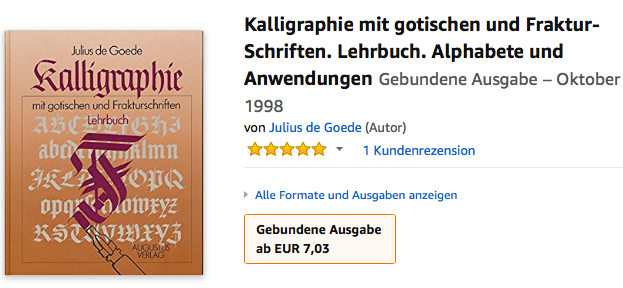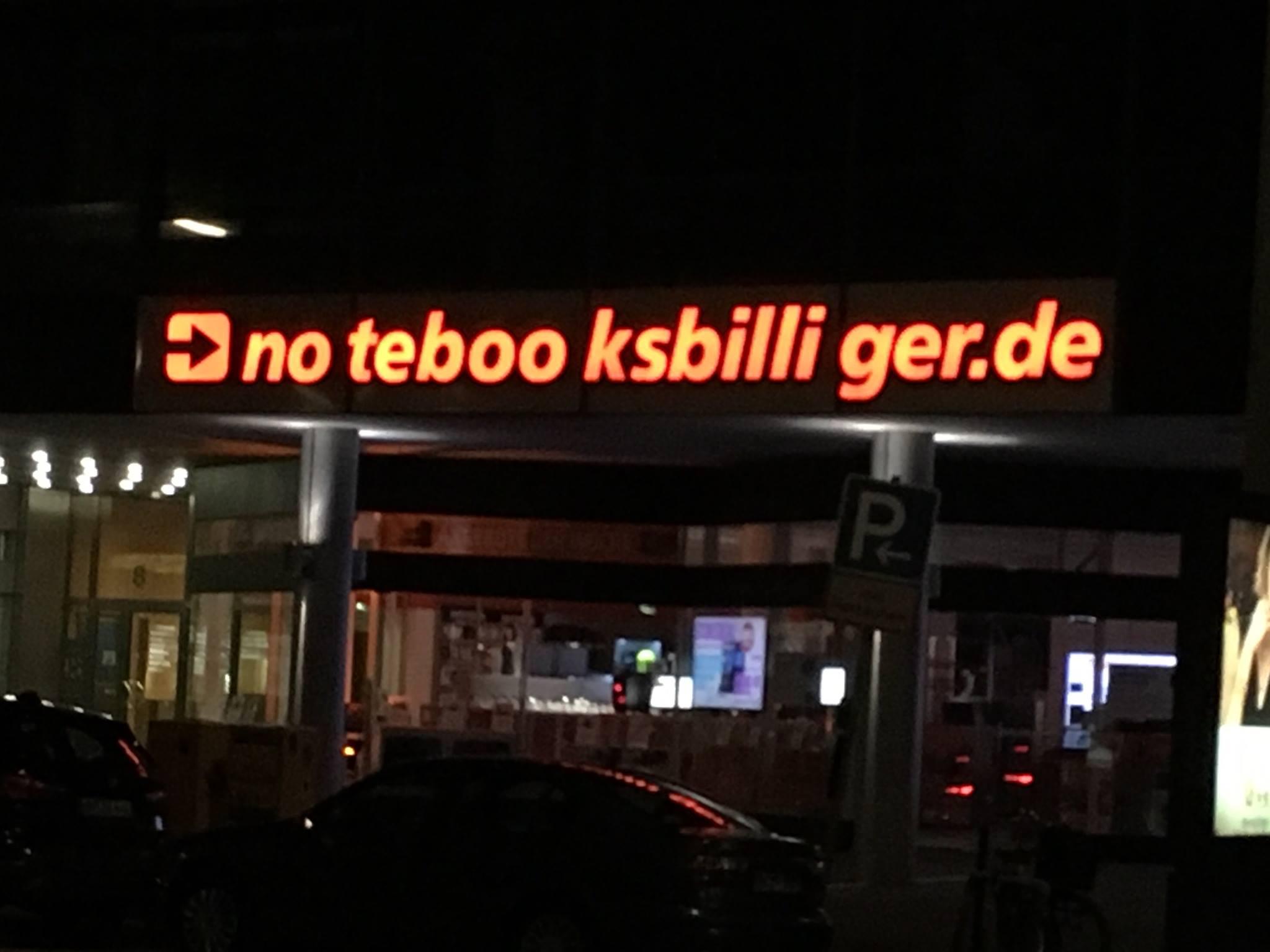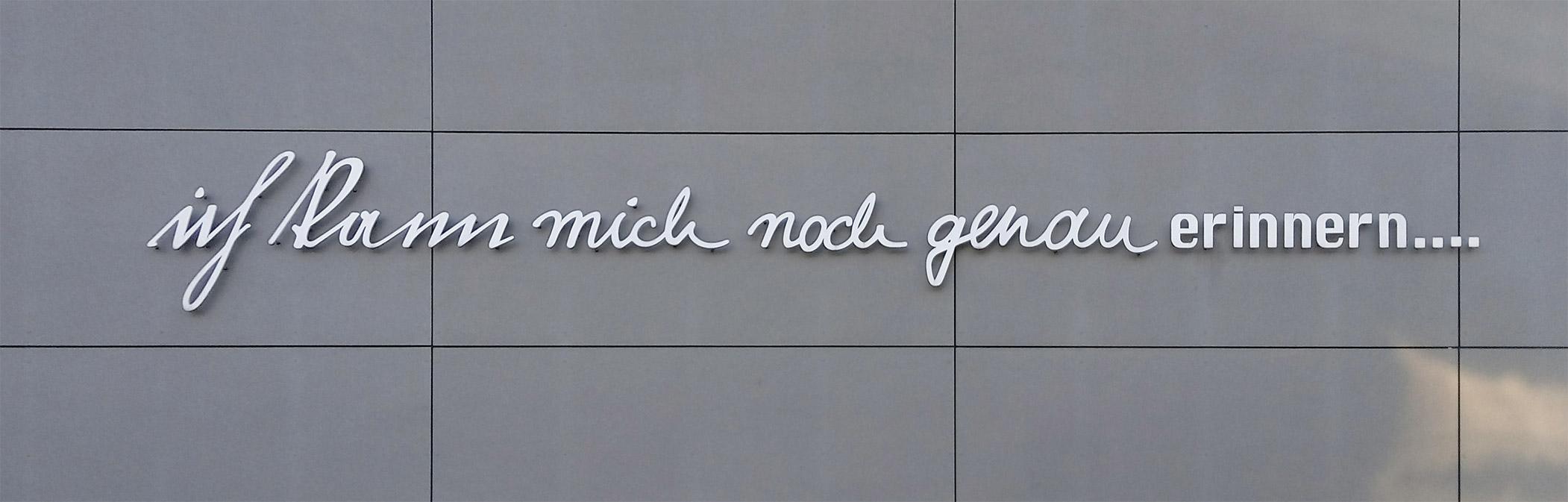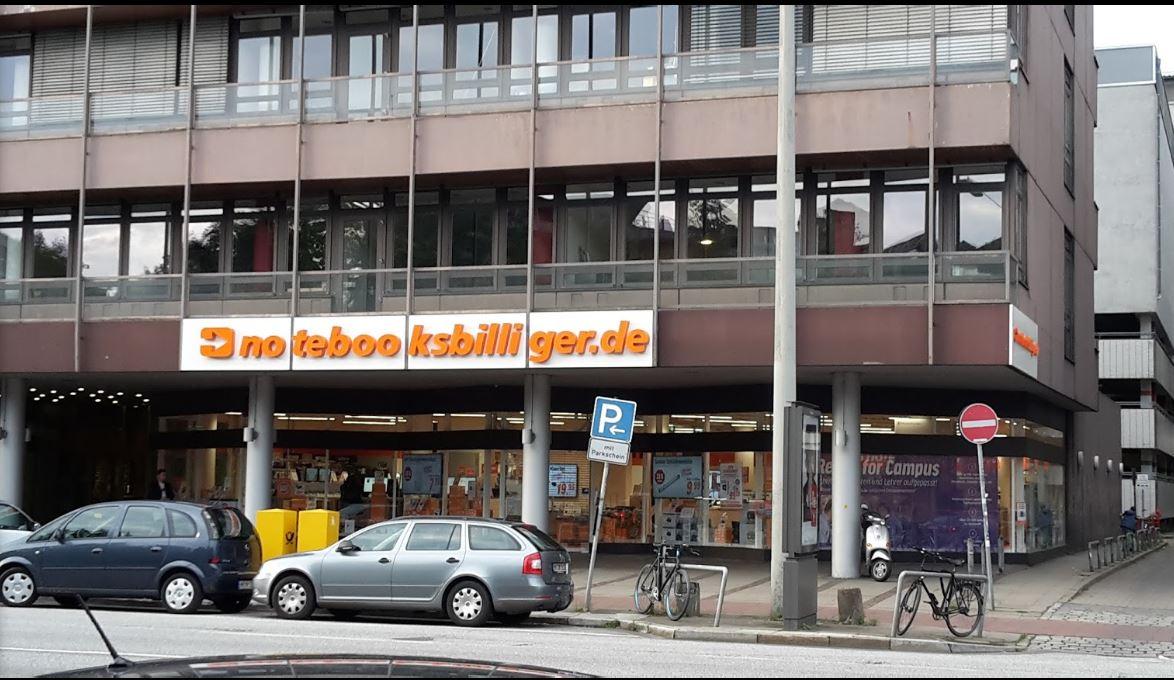
Kalligrafie ist anscheinend auch so‘ne coole neue Art von Lettering, äquivalent zu Letterpress im Nachbarstrang :-o
Ja genau – ist doch alles mit Schreiben und so. :nicken:;-)
Ne, gibt’s schon länger – seit 22 Jahren ungefähr 8-)
Ich dachte du wolltest auf das f statt ph hinaus  :-)
Nö, des Rätsels Lösung ist die Fugenbreite der Platten, auf denen die Leuchtschrift angebracht ist. Hätte man sicher auch schöner lösen können.
Nun ja, schon irgendwie schlimm... ABER kann es nicht sein, das gerade dieses Rätsel: "no teboo...??? Wie jetzt,. kein Taboo?" dazu führt, dass viele stehen bleiben und einige Zeit daran herumstottern, bis sie letztlich entdecken, das ist ein Laden von Notebooks billiger.de - und schon hat sich die URL im Hirn eingebrannt.
Und schon machen wir und andere Seiten, welche dieses Typo-"Missgeschick" zeigen wieder kostenlos Werbung für den Laden.
Ich würde mal sagen: Happy Accident...
Naja, man kann sich auch alles schön reden. Das wird sicherlich nicht so geplant sein. Wahrscheinlich war das die billigste und einfachste Lösung, weil diese Platten schon da waren. Man kann sich etwas einprägen und man möchte sich mit etwas beschäftigen, wenn es schnell und einfach wahrnehmbar ist. Irritationen können auch wirken, sollten dann aber auch offensichtlicher sein … Murks ist Murks
Das ist schon richtig, geplant ist das garantiert nicht, und Murks ist es auch. Schö reden wollte ich das nicht, sondern hatte eben das gefühl, dass solch stümperhafter Murks gelegentlich auch dafür gut ist, sich an so einen b esser erinnern zu können, und dann eben doch einen wirtschaftlich überraschenden Nebeneffekt hat.
Beispiel: in den frühen 1970er Jahren traf ich auf einen An-und -Verkauf-Laden, der eben auch ein ziemlich stümperhaftes Ladenschild hatte, auf dem dieses An und Verkauf teils horizontal, silbenweise, teils vertikal auf dem Schild verteilt war, und man über 3 Zeilen VER AKA NUF  lesen konnte. Auch das erschoss sich erst nach einiger Rätselei. Ich habe bestimmt viele soche Gebrauchtwarenläden gesehen, die meisten vergessen, an den aber erinnere ich mich, inclusive der Adresse bis heute.
Doch zurück zu den Notebooks: Das Seltsame: auf dem Nacht-Foto schaut das nicht aus, als ob der Schriftzug um die Ecke geht, anders als der gleiche Murks auf @Phoibos' Tagesbild. Also scheint es diesen Murks gleich mehrfach zu geben?
Des Rätsels Lösung: Das Gebäude hat keine Kurve. Dieses Kurvenphoto ist wahrscheinlich mir irgendeiner Panoramadingsbumsoption gemacht worden. Die Leuchtreklame hängt da schön gerade an der Hausfront.
Edith/Ergänzung. Auf alten Fotos (da war mal u.a. Schlecker) kann man auch sehen, dass es offensichtlich keine zwingende Bau- resp. Gestaltungsvorschrift gibt, die Leuchtelemente genau zwischen die Längsraster zu hängen. Man hätte durchaus eine durchgehende Front hängen können.
ein Punkt zu viel
Und eine Lücke zu wenig …
An einem Archiv in Planegg (München).